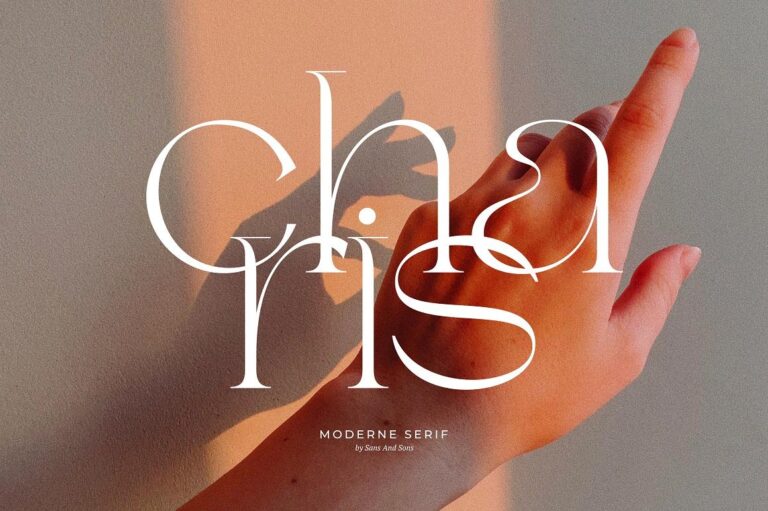
Charis – Moderne Serif Font một kiểu chữ hiện đại và thanh lịch.
Giới thiệu một kiểu font serif hiện đại “Charis Moderne” mới với phong cách thanh lịch, font chữ này là sựa lựa chọn hoàn hảo cho việc xây dựng thương hiệu, biểu tượng, thiệp mời, tiêu đề, bìa sách, tạp chí, trang web hoặc bất kỳ thiết kế nào khác.
Với các nét chữ được thiết kế mảnh, một số cạnh sắc nét, một số ký tự được vẽ ấn tượng mang lại cảm giác hiện đại và thích hợp cho nhiều các thiết kế hiện nay.
Đặc điểm:
- Multilanguange
- Alternates
- PUA Encoded
Charis – Moderne Serif Font Preview